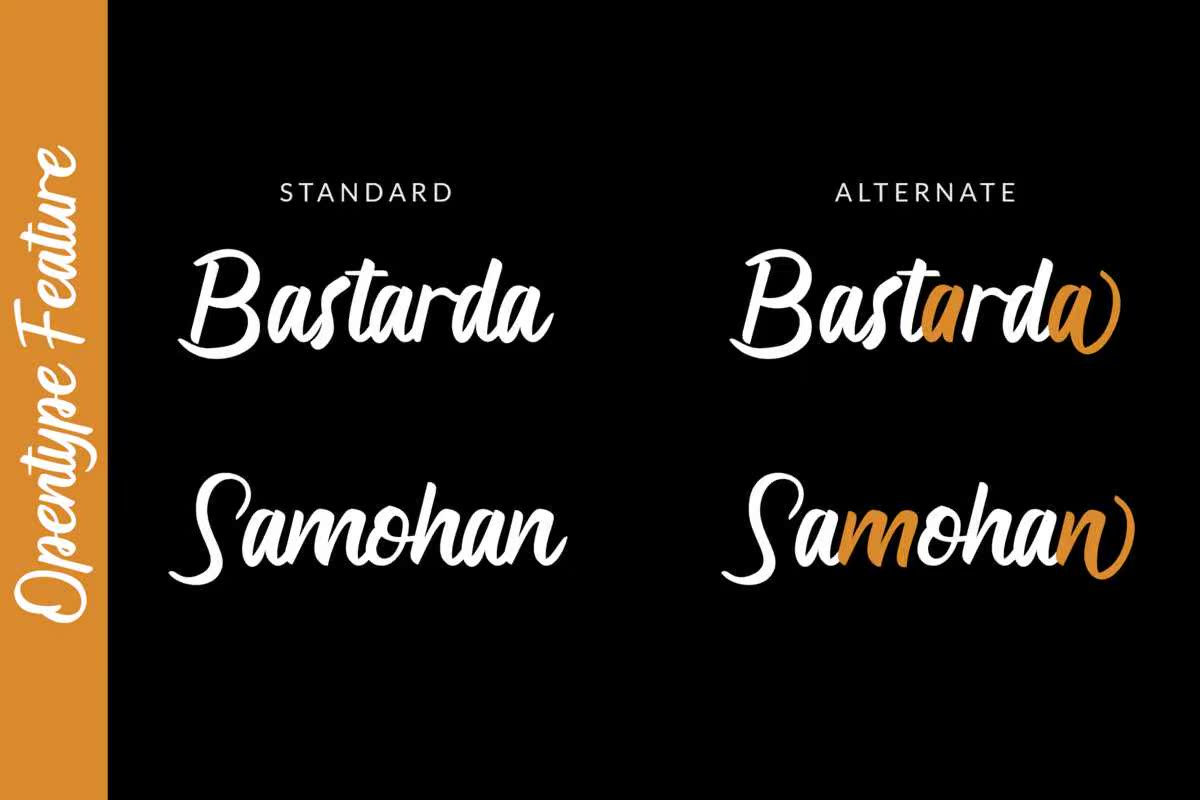
AngHoraisa RushScriptFont具有动态和节能字体。它可以用于各种用途,如标题、签名、标识、t恤设计、信头、标牌、标签、时事通讯、海报、徽章以及其他需要独特、醒目字体的设计。AngHoraisa RushScriptFont具有动态和节能字体。它可以用于各种用途,如标题、签名、,标识、t恤设计、信头、标牌、标签、时事通讯、海报、徽章以及其他所有需要独特醒目字体的设计。